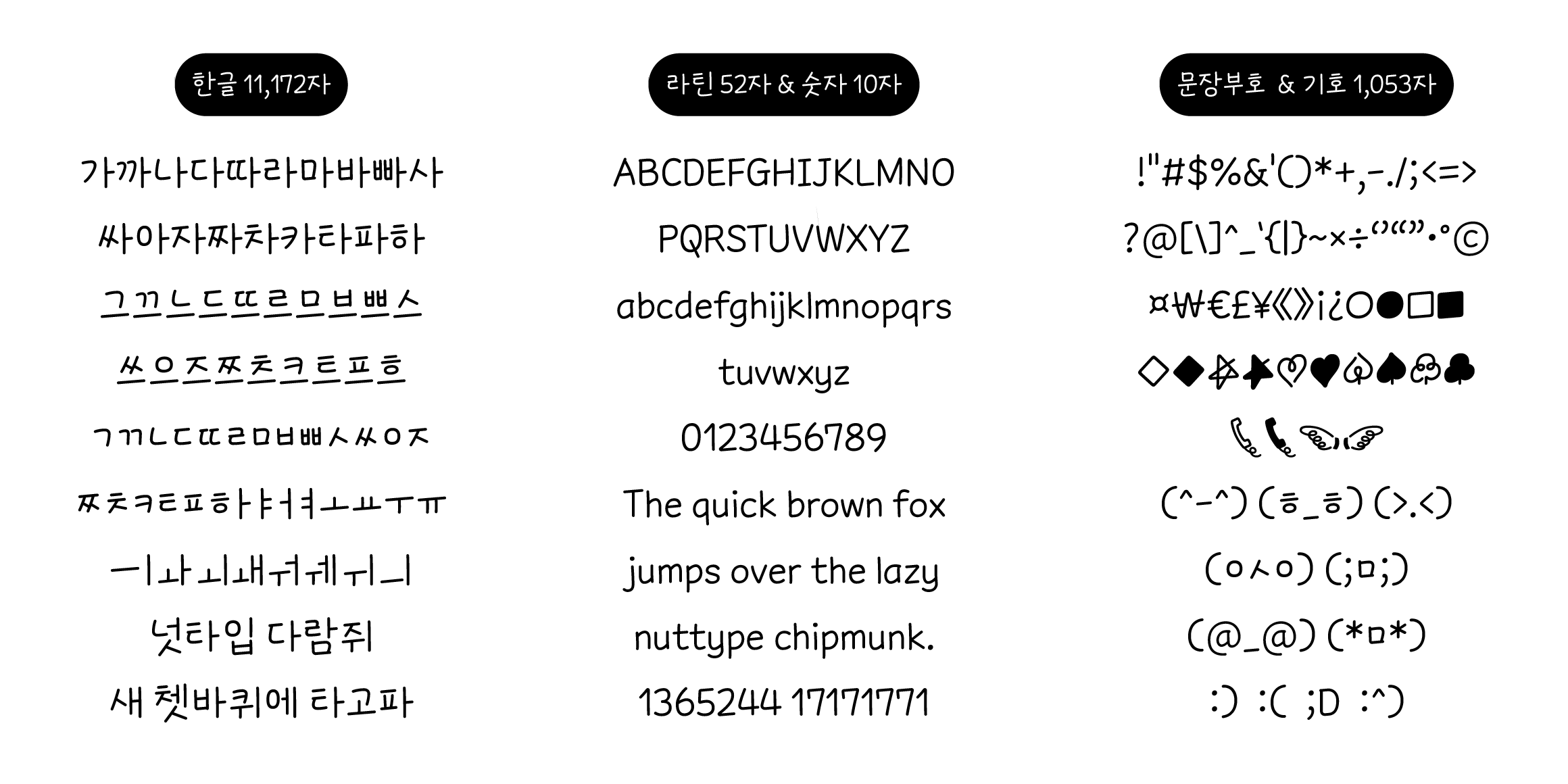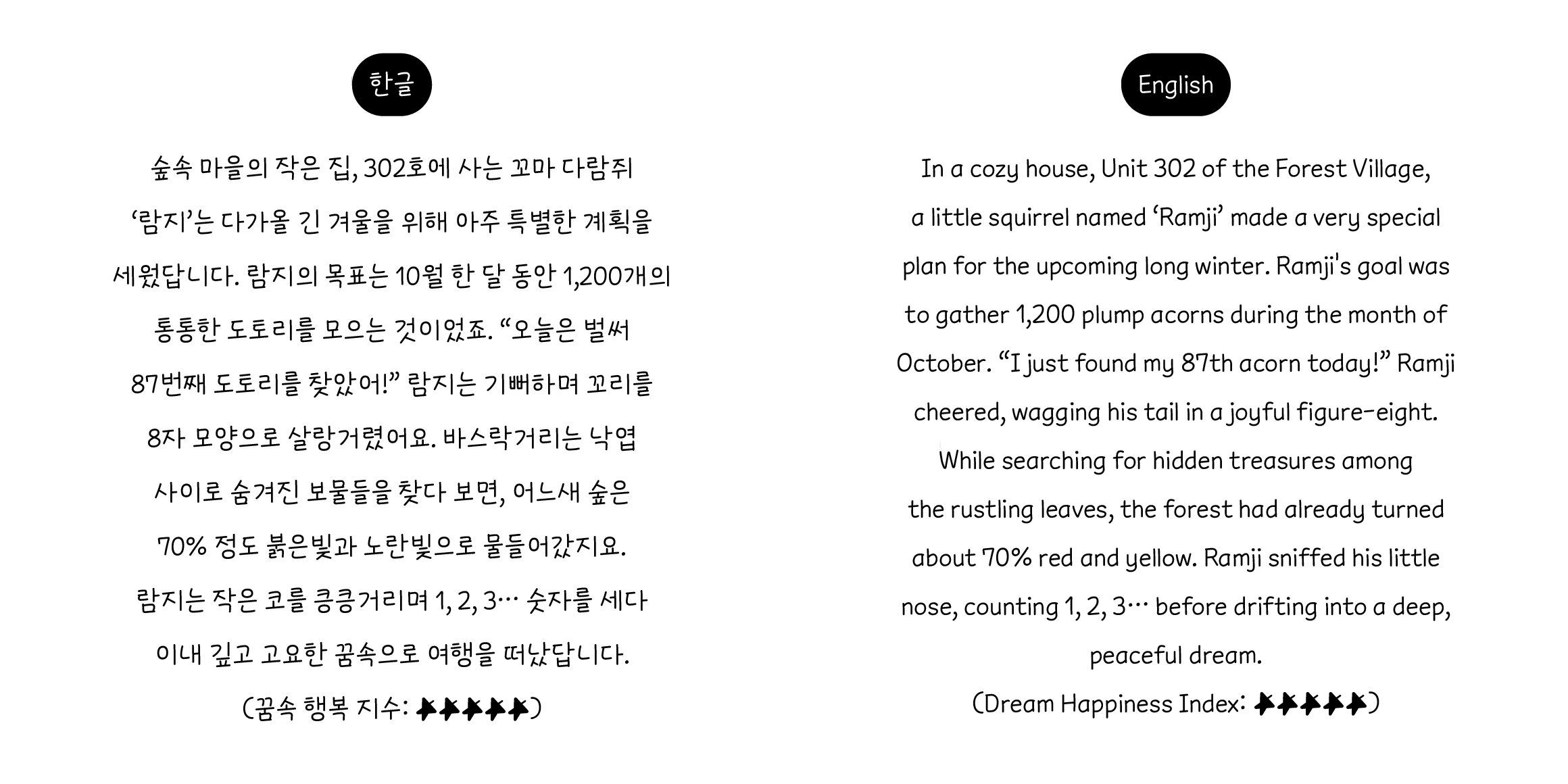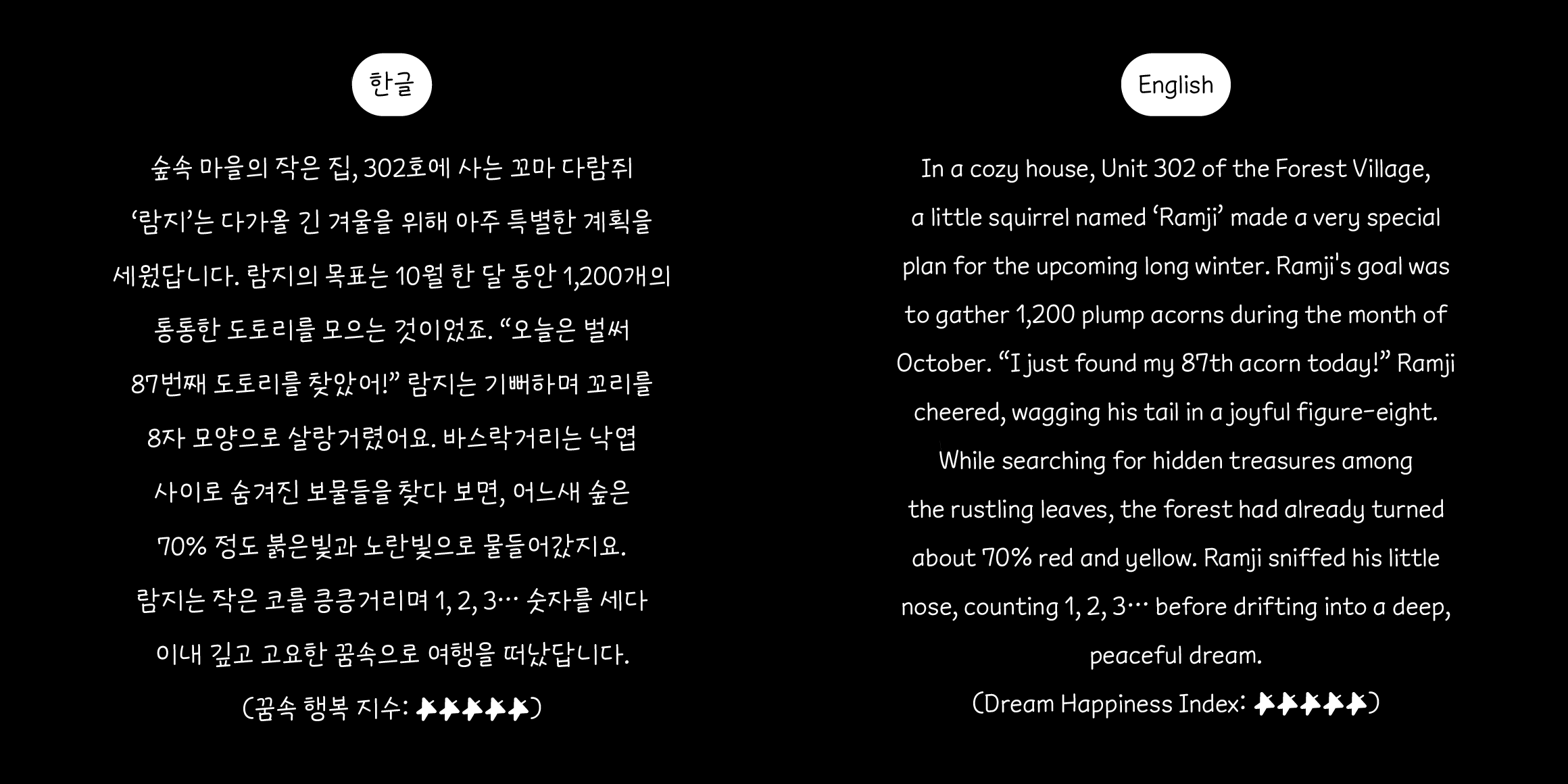
nut 개강한람지
Nuttype
분류 Script,디스플레이,손글씨
nut 개강한람지 font in use
대학생이 왜 강한지 알아? ⋯개강하니까!
방학은 눈 깜빡하니 사라졌다. 이젠 정말 받아드려야 한다. 개강이 왔음을.
눈물을 머금고 사과 패드를 꺼낸다. 이번 학기의 다짐을 하나하나씩 써 내려간다.
나는 할 수 있다. 나는 개강한 람지니까.
• 한글 11,172자 / 라틴 52자 / 부호 1,053자 / 숫자 10자
• nut 개강한람지 / nut Super Strong Ramji